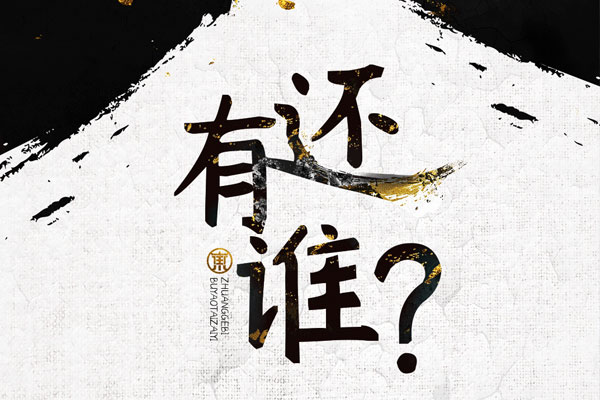
杨任东竹石体-Bold
杨任东竹石体是一款融合中国风底蕴与手写质感的古典手写体,以端庄优雅的风格见长,自2017年世界知识产权日发布以来,便成为设计领域兼具文化韵味与实用性的优选字体。 杨任东竹石体字形方正稳健,重心居中、中宫适中的结构设计,让字体在视觉上平衡舒展,兼具沉稳与灵动;笔型设计尤为独特,笔画间点缀竹节纹理装饰元素,古典意象与自然质感交融,细节处尽显东方美学巧思。整体呈现中等粗细,笔画均匀规整,断开式连接的处理既保留手写体的随性,又不失结构的严谨,适合营造雅致内敛的视觉氛围。 作为免费商用字体,杨任东竹石体以GB2312-80字符集为基础,增补常见汉字,覆盖50000余字符,支持多场景应用——无论是海报标题、产品包装,还是品牌logo、网页设计,均能以手写风传递端庄气质。7个字重选择更适配不同排版需求,让设计既具文化个性,又无版权顾虑,是中国风设计的理想字体选择。